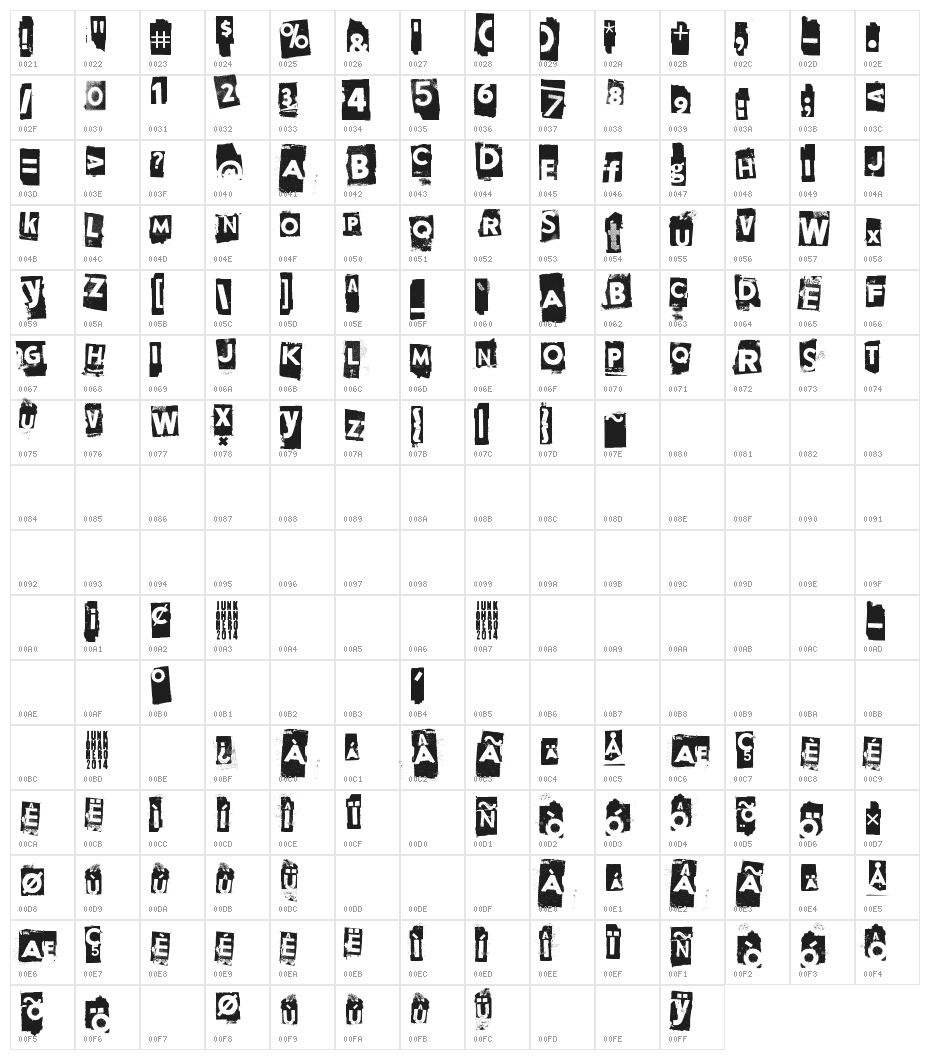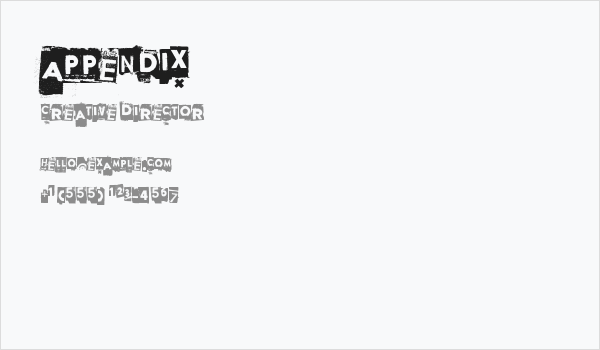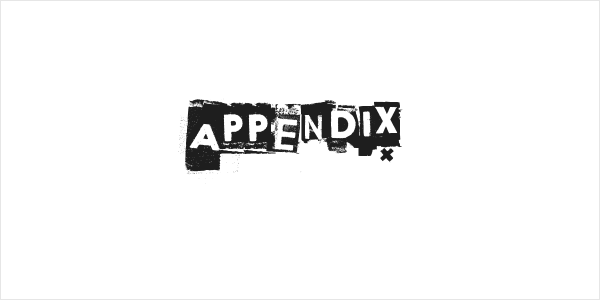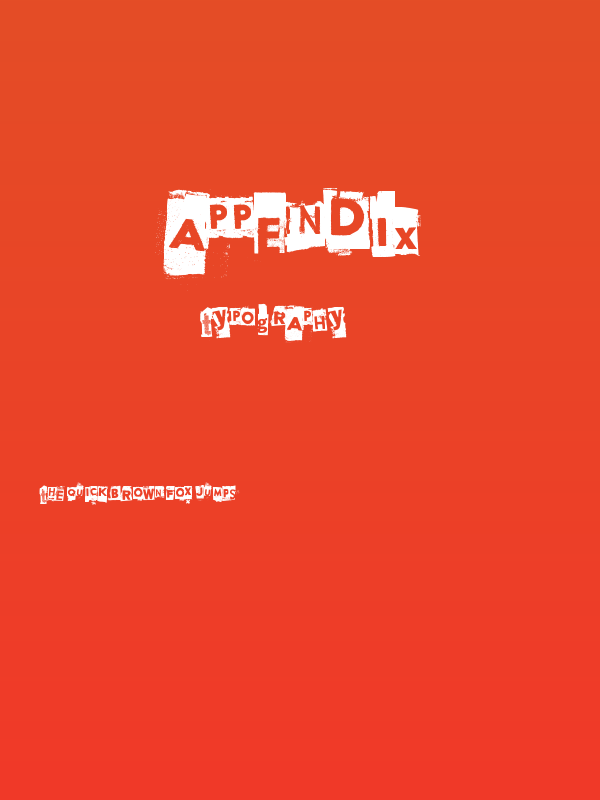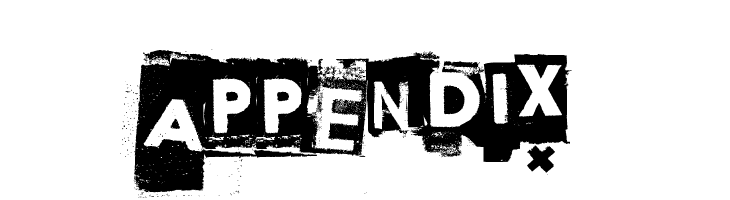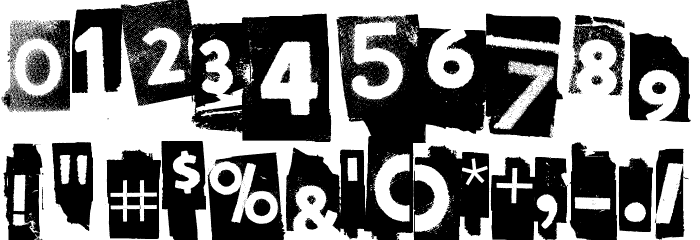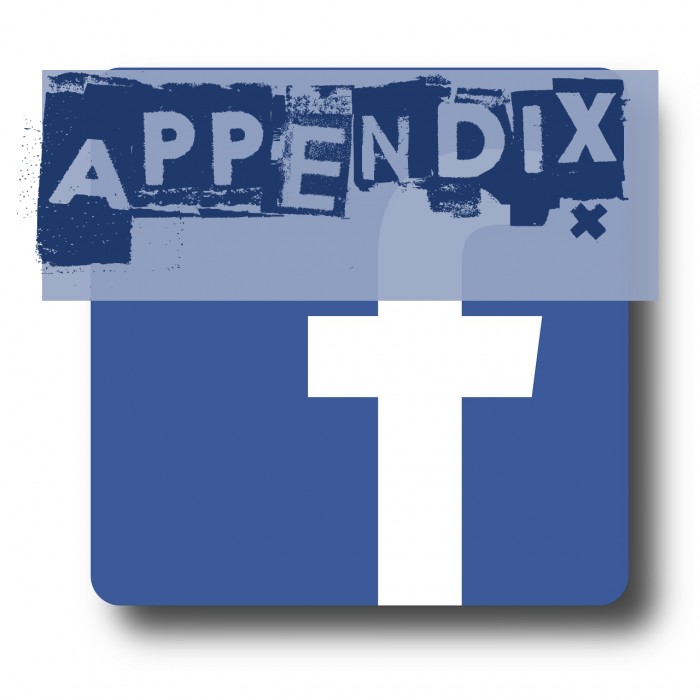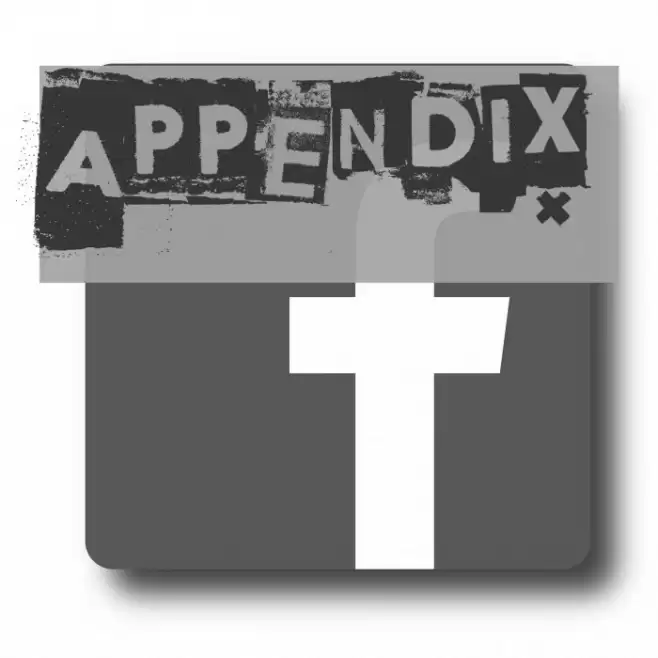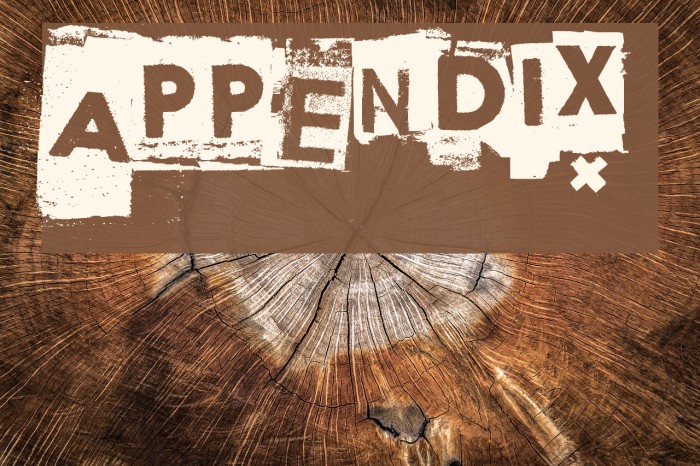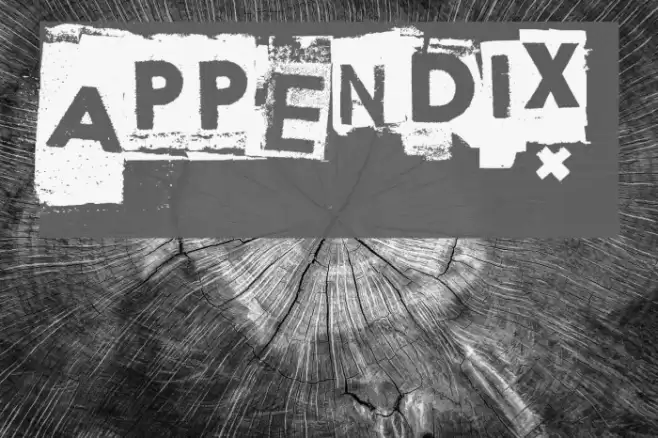
Appendix Font
✎ Distorted Eroded
| Категория | Distorted Eroded |
| Рекомендуемые проекты | Ideal for posters, album covers, and designs needing a gritty, urban aesthetic. |